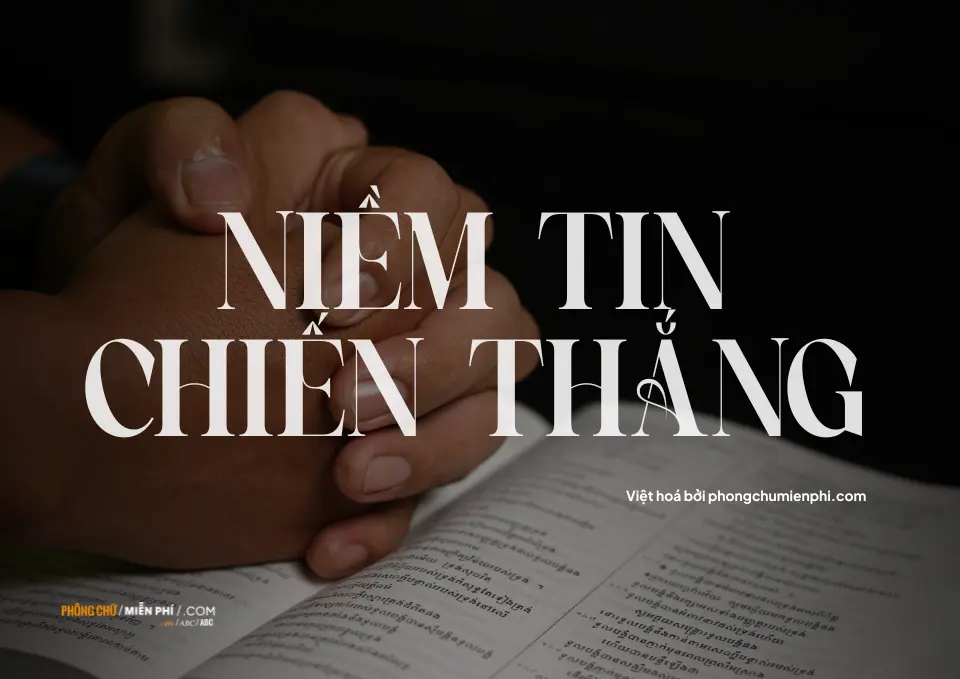
Tên font: Font Việt hoá HEROEAU ELEGANT
Font Việt hoá PCMP HEROEAU ELEGANT
Phông chữ PCMP HEROEAU ELEGANT là phông chữ serif sang trọng. Tạo nên những tiêu đề sang trọng, lộng lẫy và thiết kế thanh lịch với phong cách cổ điển. Thiết kế đầy phong cách của phông chữ này hoàn hảo để tạo nên cảm giác cổ điển và đương đại cho các dự án của bạn. Các đường nét tương phản và phần đuôi cong của phông chữ mang đến vẻ ngoài bóng bẩy, thanh lịch cho logo, thiệp chúc mừng, thiệp cưới, trích dẫn, quảng cáo, v.v.